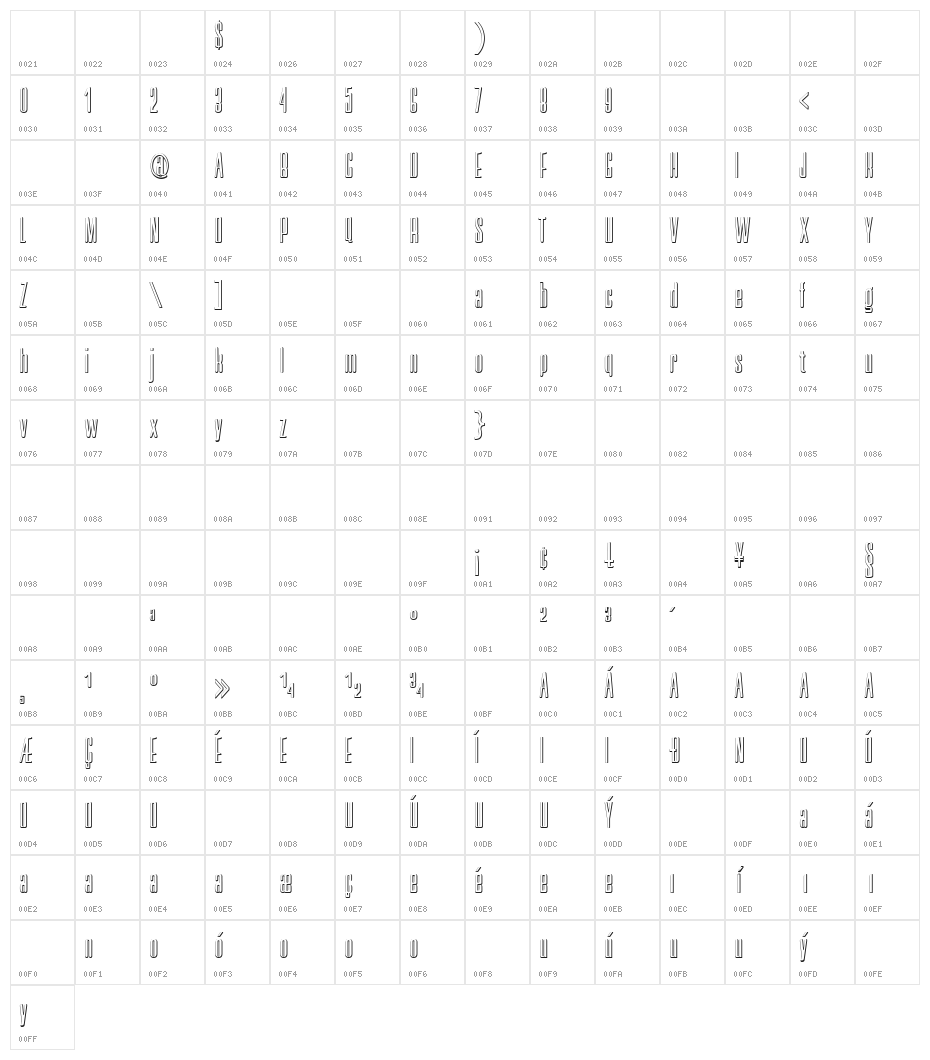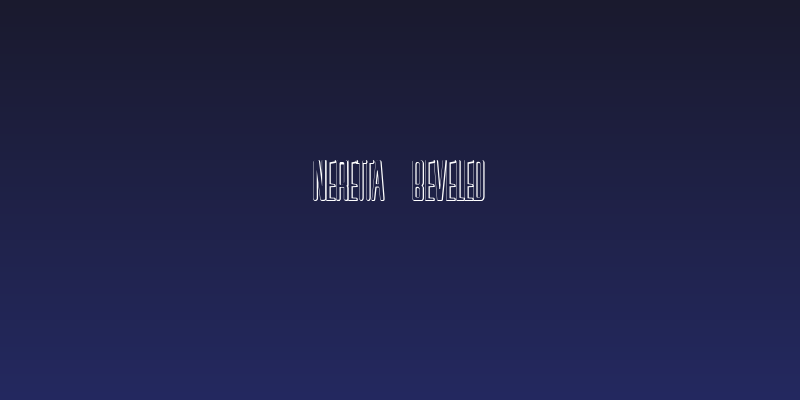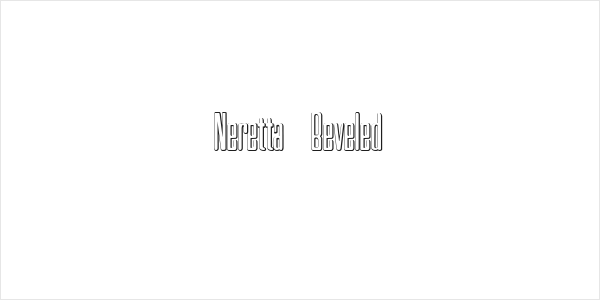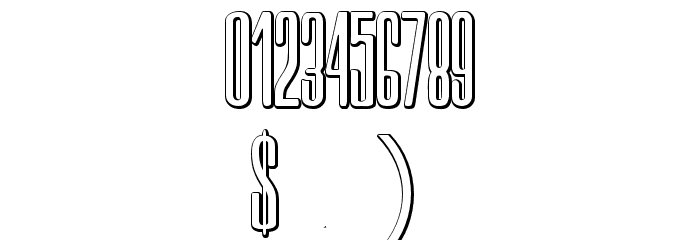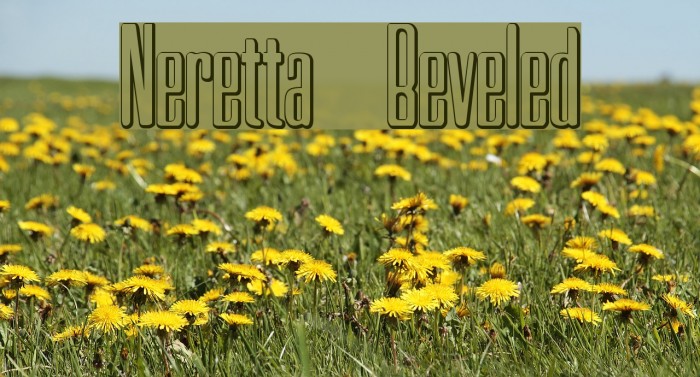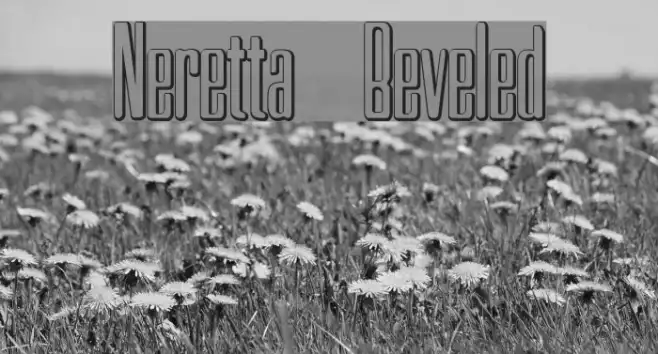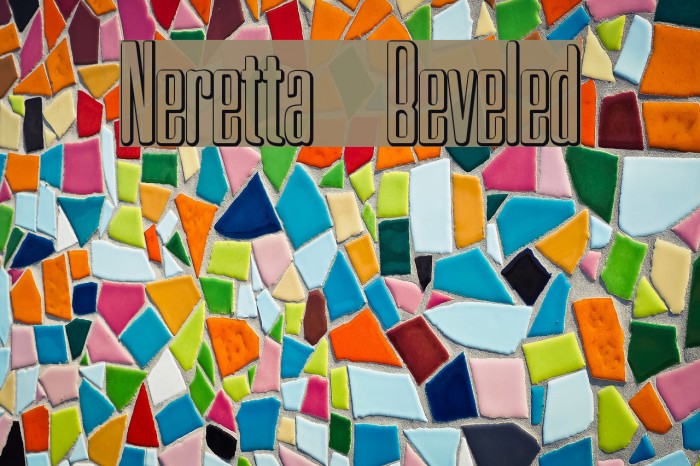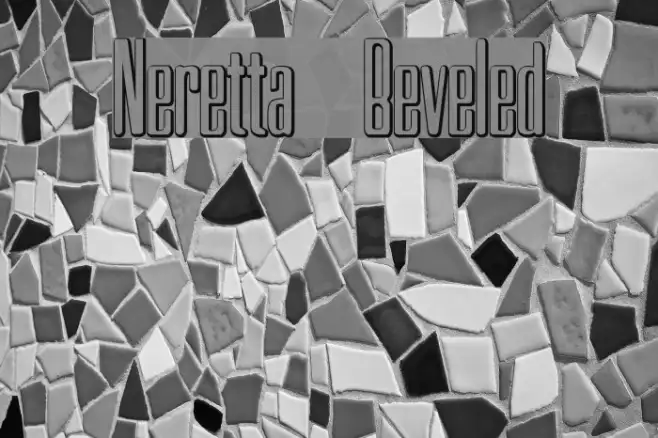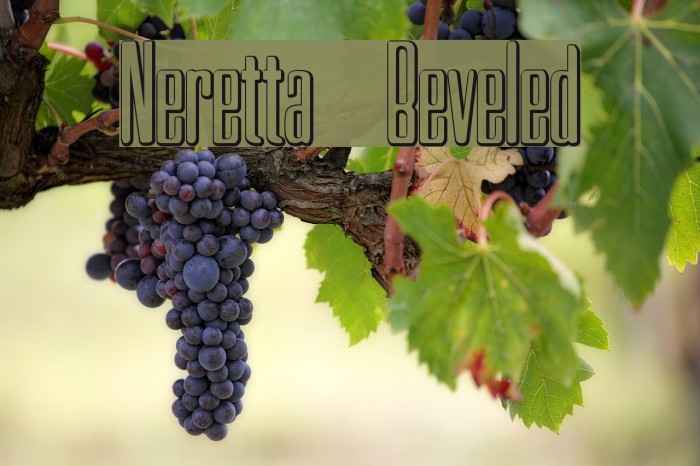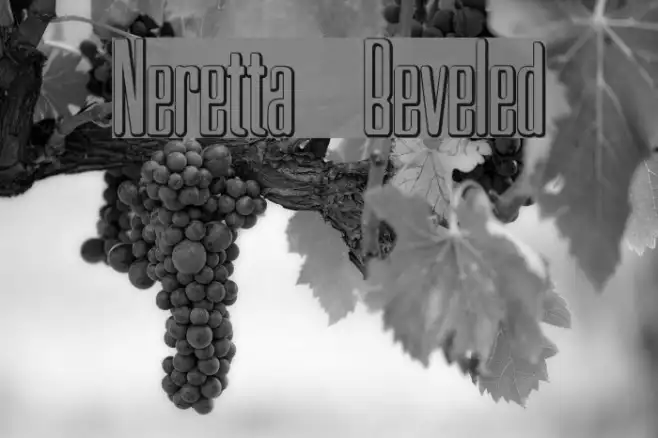
Neretta Beveled Font
| Gesamtstil | Modern, Decorative |
| Vorgeschlagene Projekte | Ideal for posters, logos, headlines, and any design requiring a striking, modern look. |